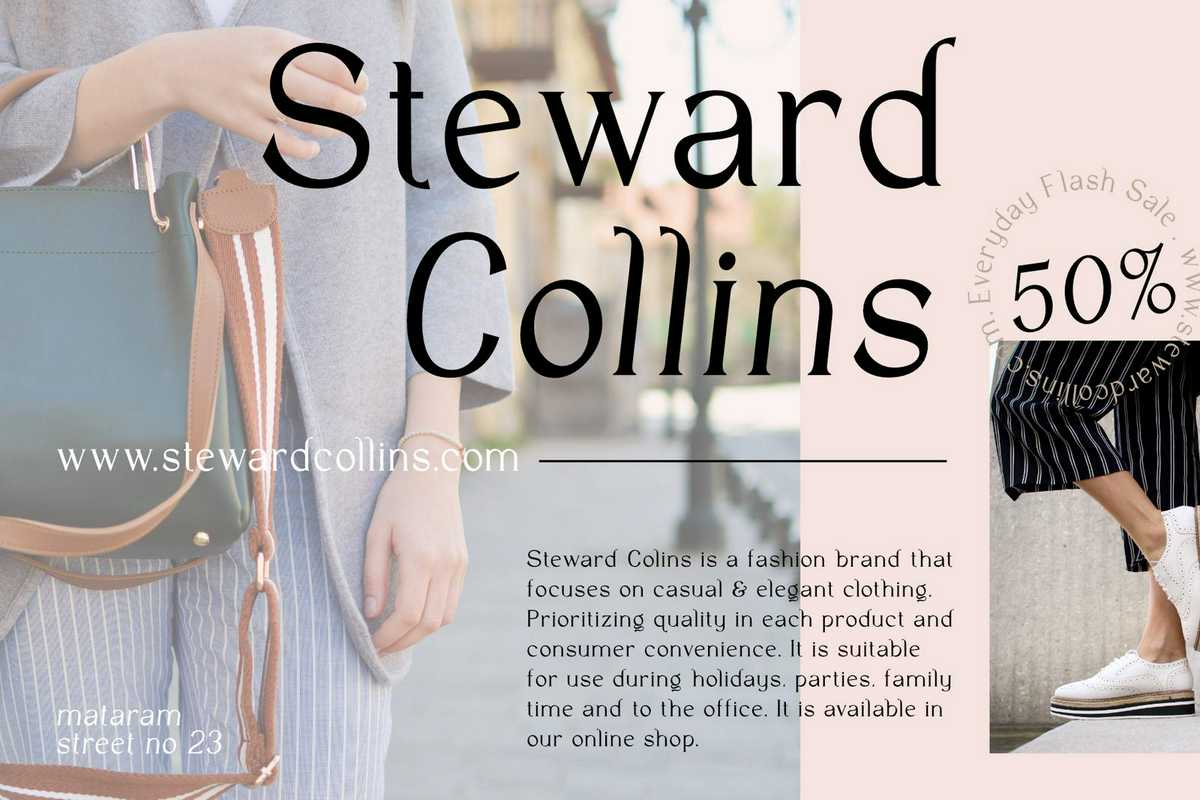
Antobeis采用现代优雅的触控技术。触控技术完美满足现代优雅布局的设计需求。共有2种款式,规则型和斜型。配备多语言工具口腔茶具,用于各种设计目的。Antobeis采用现代优雅的触控技术。触控技术完美满足现代优雅布局的设计需求。共有2种款式,常规和倾斜。配备多语言工具口腔茶具,用于各种设计目的。